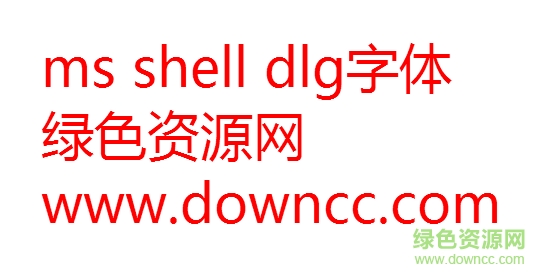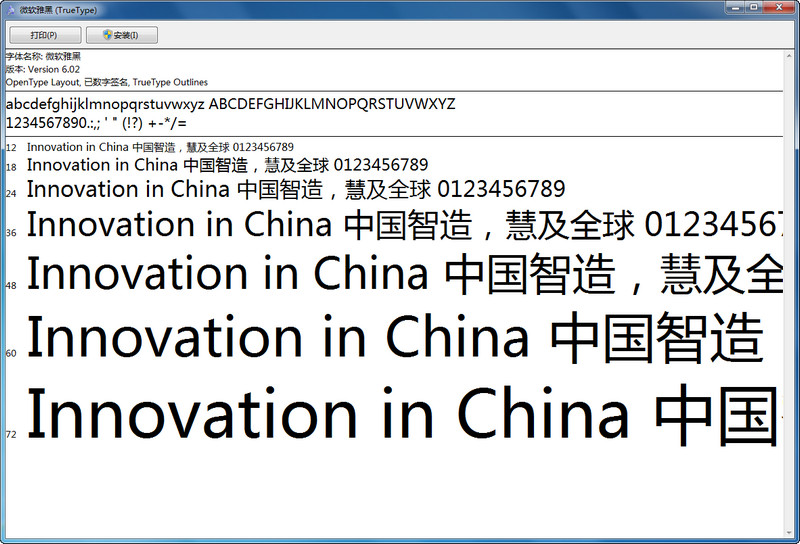
ms shell dlg字體是系統(tǒng)的一款默認(rèn)字體,簡(jiǎn)潔明亮的形體讓你的文字內(nèi)容有著極佳的視覺體驗(yàn),受到很多網(wǎng)友的喜歡,而且這款字體也非常的實(shí)用,適合絕大多數(shù)編輯文字信息的用戶使用,感興趣的朋友就來(lái)綠色資源網(wǎng)即可免費(fèi)下載哦!
默認(rèn)的字體是MS Shell Dlg(8),而MS Shell Dlg本身并不是一種字體,只是一種字體映射。以中文Windows XP平臺(tái)為例,MS Shell Dlg(8)即為宋體(9.5)。映射的字體在注冊(cè)表中可以指定,好處是可以動(dòng)態(tài)更改其他應(yīng)用程序的字體--當(dāng)然前提是使用這個(gè)字體映射的vc 對(duì)話框字體指定是在.rc資源文件中指定。
大家需要的ms shell dlg只是系統(tǒng)中的默認(rèn)字體,而大部分的系統(tǒng)默認(rèn)字體均是“微軟雅黑”,小編為大家?guī)?lái)該款字體的下載鏈接,歡迎大家免費(fèi)體驗(yàn)!
MS Shell Dlg 字體的刷新速度要比實(shí)際指定的其他字體速度慢,所以在某些情況下會(huì)顯示不正常,所以在程序中盡可能要少用這樣的字體而是指定為具體的字體,如宋體等,使用宋體的刷新速度就比較快,減少了尋找映射的時(shí)間。